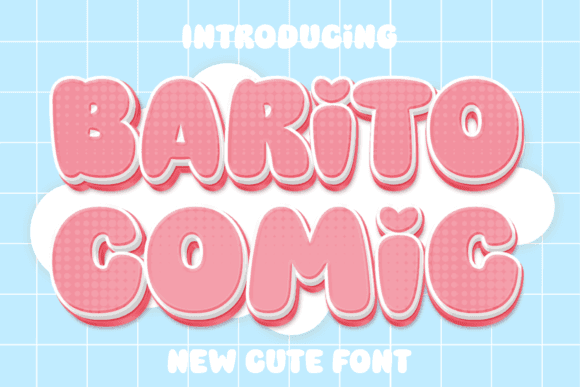
Fuente cómica Barito para carteles y diseños de camisetas divertidos
Fuente de cómic Barito
Barito Comic es una fuente de exhibición encantadora y divertida, caracterizada por su estilo regordete y caprichoso. Esta tipografía es perfecta para proyectos que requieren una estética divertida y accesible, y atrae tanto a niños como a adultos gracias a su diseño alegre y jovial. Ideal para libros infantiles, juegos y materiales educativos, donde una fuente bonita y divertida puede cautivar y deleitar al público infantil.